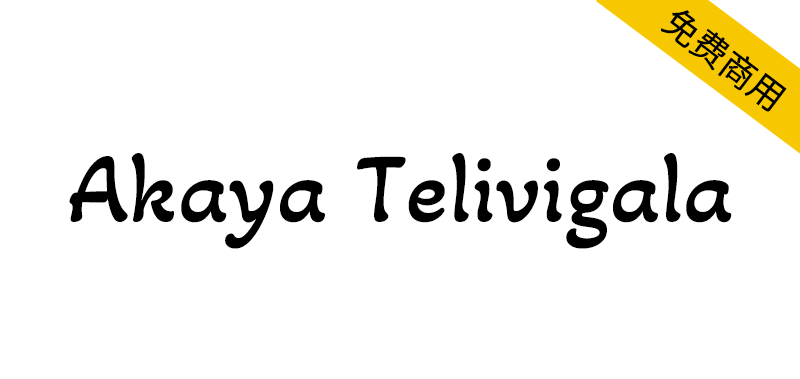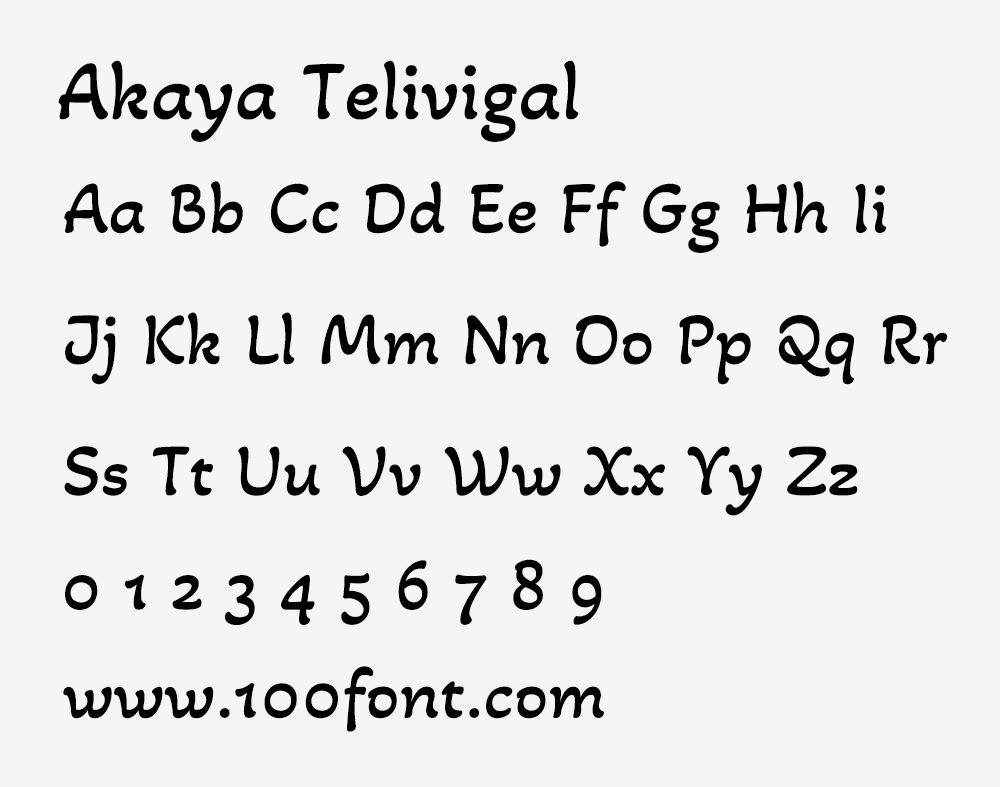
Akaya是一种单一粗细的实验性字体,使用卡纳达语、泰卢固语和拉丁文字。Akaya Telivigala和Akaya Kanadaka是两个独立的字体文件,它们共享一个共同的拉丁语。
关于Akaya:泰卢固语和卡纳达语的文字可以追溯到高度风格化的卡丹巴文字。在接下来的几个世纪里,这些文字受到历代王朝的庇护,他们多次重新解释这些文字。这些解释在本质上越来越务实,在很大程度上消除了结构上的复杂性。
这种简化被早期的基督教传教士更进一步,他们为这些剧本制作了第一个主角类型。然而,当他们这样做的时候,他们引入了一种受铜版启发的笔划调制方法来调制这些字符,在那之前,这些字符在本质上基本上是单线的。这些字体的笔划调制是沿着横轴的。这里的字母形状是几何的和构造的。传教士的这些早期实验仍然是最广泛接受的风格,在文本设置中效果良好。
当人们环顾今天在书名、涂鸦或宣传告示上发现的手写泰卢固语或卡纳达语景观时,一种反复出现的书法风格是显而易见的。这似乎与刻板、正式的文本风格截然不同。这里的字母形状更流畅,比例也更大方。笔划调制和对角线重音呼应了拉丁书法,适用于卡纳达语和泰卢固语。Akaya是基于这种生动的手写风格。
Akaya的字母形状试验了反向导管,每个字符的书写方向都是反向的,以增加流动性。阿卡亚拉丁语也采用了相同的原理和对比角度,这取决于字母的结构。这形成了其特征形状的基础。
Akaya is a single weight experimental display typeface in Kannada, Telugu and Latin scripts. Akaya Telivigala and Akaya Kanadaka are made as two separate font files which share a common Latin.
About Akaya
Telugu and Kannada scripts trace their origins to the highly stylised Kadamba script. Over the following centuries, these scripts were patronised by successive dynasties who reinterpreted this script several times. These interpretations were increasingly pragmatic in nature, stripping off structural complications to a great degree.
This simplification was taken a step further by the early Christian missionaries who made the first lead types for these scripts. However, when they did this, they introduced a copperplate inspired stroke modulation to these characters which were largely monolinear in nature till then. The stroke modulations in these founts followed the horizontal axis. The letter shapes here were geometric and constructed. These early experiments by the missionaries remains the most widely accepted style and works well for text settings.
When one looks around the hand-written Telugu or Kannada landscape today, found on book titles, graffiti or propaganda notices, a recurring calligraphic style is evident. This appears quite distinct from the rigid, formal text styles. The letters’ shapes here are more fluid and proportions more generous. The stroke modulations and the diagonal stress echo Latin calligraphy and work well for both Kannada and Telugu scripts. Akaya is based on this lively hand-written style.
The letter shapes for Akaya experimented with reverse ductus, where each character is written with its stroke direction reversed to add fluidity. The same principle and contrast angle is applied in Akaya Latin, depending on the structure of the letter. This is forms the basis for its characteristic shapes.